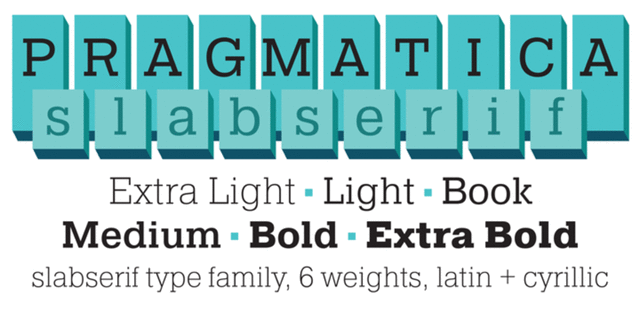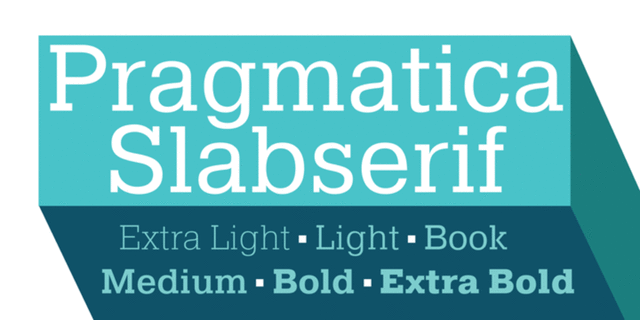
Pragmatica Slabserif (6)
Опис гарнітури Pragmatica SlabserifГарнитура Прагматика Слабсериф разработана на основе популярной гарнитуры Прагматика (дизайнеры Владимир Ефимов, Изабелла Чаева, 1989–2004) путем добавления к ней брусковых засечек, аналогично тому, как шрифт Helserif (дизайнер Phil Martin, 1978) образован добавлением засечек к гарнитуре Helvetica (дизайнеры Эдуард Хоффман, Макс Мидингер, 1957). Первые эскизы шрифта были сделаны Владимиром Ефимовым в 1988 году при разработке гарнитуры Прагматика, на основе которых Ольга Умпелева создала брусковый шрифт в шести начертаниях. Все начертания Прагматики Слабсериф согласованы с соответствующими начертаниями Прагматики по размерам, пропорциям, насыщенности и характеру рисунка и могут применяться как совместно с ней, так и самостоятельно. Прагматика Слабсериф может быть полезной для набора текстов технического характера, для использования в журналах, газетах, корреспонденции, а также в рекламе и акциденции. Гарнитура выпущена компанией ПараТайп в 2011 году.
Хіт 1990-х Pragmatica Slabserif підтримує 84 мовиУкраїнська, Англійська, Німецька, Французька, Польська, Португальська, Іспанська, Французька, Російська, Чеська, Голландська, Італійська, Шведська, Турецька, Фінська, Білоруська, Сербська, Болгарська, Естонська, Литовська, Албанська, Африкаанс, Баскська, Бретонська, Валенсаска, Galician, Гельська (Шотландська), Данська, Індонезійська, Ірландська, Ісландська (Win), Каракалпацька, Каталонська, Норвезька, Окситанська, Ретороманська, Самі Лулі, Тсванська, Узбецька (Лат.), Фарерська, фризька, Чаморро, Естонська (Win), Південносаамська, Албанська (Win), Угорська, Верхньолужицька, Карельська, Латвійська (Mac), Литовська (Mac), Маорійські (Mac), Молдавська (Лат.), Нижньолужицька, Румунська (Win), Словацька, Словенська, Туркменська (Лат.), Хорватська (Win), Естонська (Mac), Курдська, Латишська, Маорійські, Абазинська, Аварська, Агульська, Адигейська, Даргинську, Інгуську, Кабардино-Черкеська, Кабардинська, Карачаєво-Балкарська, Кумицька, Лакська, Лезгинська, Македонську, Мордовсько-Мокшанська, Мордовсько-Ерзянська, Ногайська, Рутульська, Табасаранська, Татська, Цахурська, Чеченська, Російська (XIX) Функції сімейства шрифтів Pragmatica SlabserifЗастосування гарнітури у верстці:
Асоціації з сімейством шрифтів Pragmatica SlabserifОсобистість і характер гарнітури:
точний, легкий, холодний, модний, діловий, стійкий, стабільний, статичний, рівний, дротяний, худий, твердий, серйозний, розумний, прямокутний, залізний, сталевий, надійний, впевнений, сильний, індустріальний, техногенний, переконливий, мотивуючий, відповідальний, авторитетний, значний, військовий, армійський, гучний, амбітний, робочий, потужний, важкий, суворий, крутий